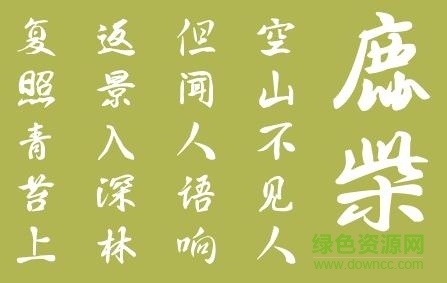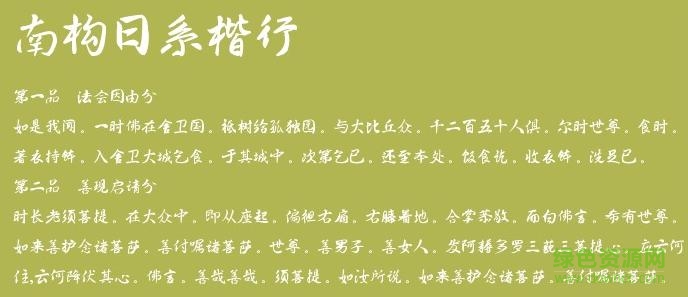
南構(gòu)日系楷行字體
南構(gòu)日系楷行體是一款融合的日本書寫方法的手寫字體,字形柔美,適合用于廣告、藝術(shù)設(shè)計(jì)等方面,可作為日系小說的字體。歡迎大家來綠色資源網(wǎng)下載使用!
南構(gòu)日系楷行體
南構(gòu)日系楷行,這是一款日本書法風(fēng)格的字體,優(yōu)雅而柔美,將日系文化融入了中文漢字結(jié)構(gòu)筆畫中,形成一種獨(dú)特的風(fēng)格。